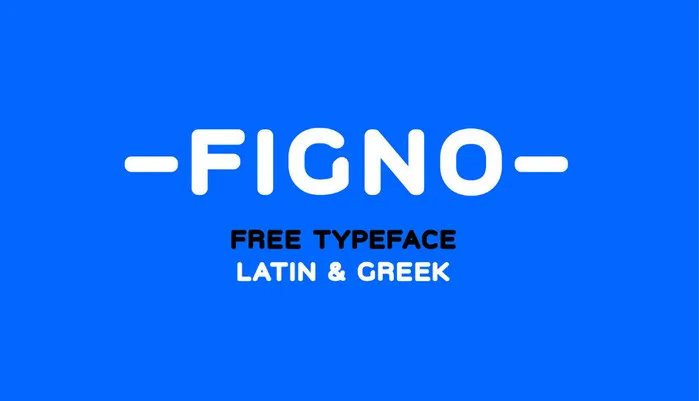
Figno Typeface – Fonte Grátis
Figno Typeface
Figno Typeface é uma tipografia sem serif desenvolvida pelo designer iordanis passas. Especialmente adequada para aplicações visuais chamativas como logotipos, títulos e design de tipografia, Figno apresenta um minimalismo refinado. Com mais de 170 caracteres disponíveis, a tipografia oferece uma variedade rica de opções que certamente complementará qualquer projeto gráfico no qual você esteja trabalhando. Seja em sua utilização como título chamativo para sua marca ou como elemento fundamental para um design editorial, Figno possui uma graça única e uma elegância aprimorada, combinando perfeitamente com uma vasta gama de outros tipos de fontes. Para designers que valorizam simplicidade e sofisticação em seu trabalho visual, Figno é uma escolha ótima para incorporar na sua paleta de recursos gráficos.